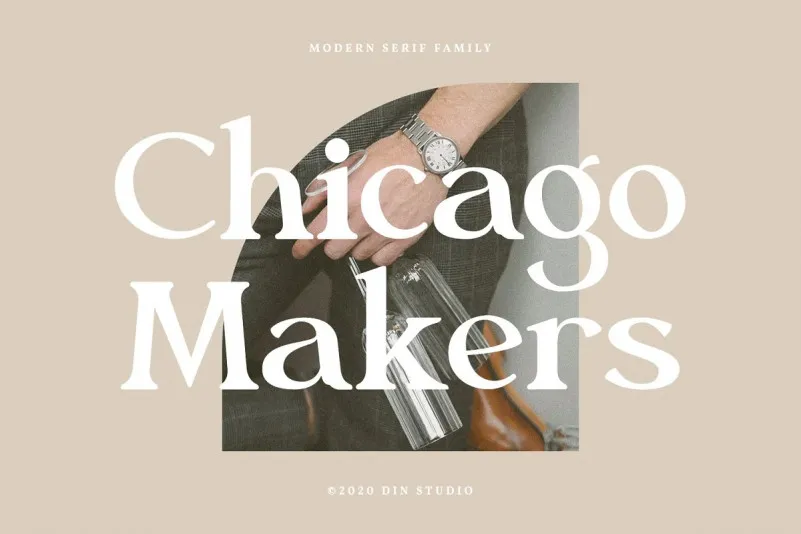
A Chicago Makers Font é uma elegante tipografia serif criada pela Din Studio, com curvas e formas equilibradas que destacam a modernidade e sofisticação dos seus projetos. Esta fonte foi desenvolvida para oferecer um visual atraente em qualquer design ou projeto que você esteja a criar. Ela é perfeita tanto para títulos, logotipos e cartões de visitas quanto para citações impressas, cartazes, embalagens, marca online ou redes sociais. A Chicago Makers Font se encaixa naturalmente em qualquer trabalho gráfico que você está a desenvolver, oferecendo um toque refinado sem comprometer a simplicidade e funcionalidade necessárias para uma grande variedade de aplicações. Experimente incorporar esta fonte aos seus designs e veja como ela reforça sua mensagem de forma elegante e moderna.